输入名字,挑一个样式,下载 PNG。就这么简单,大约十秒钟。
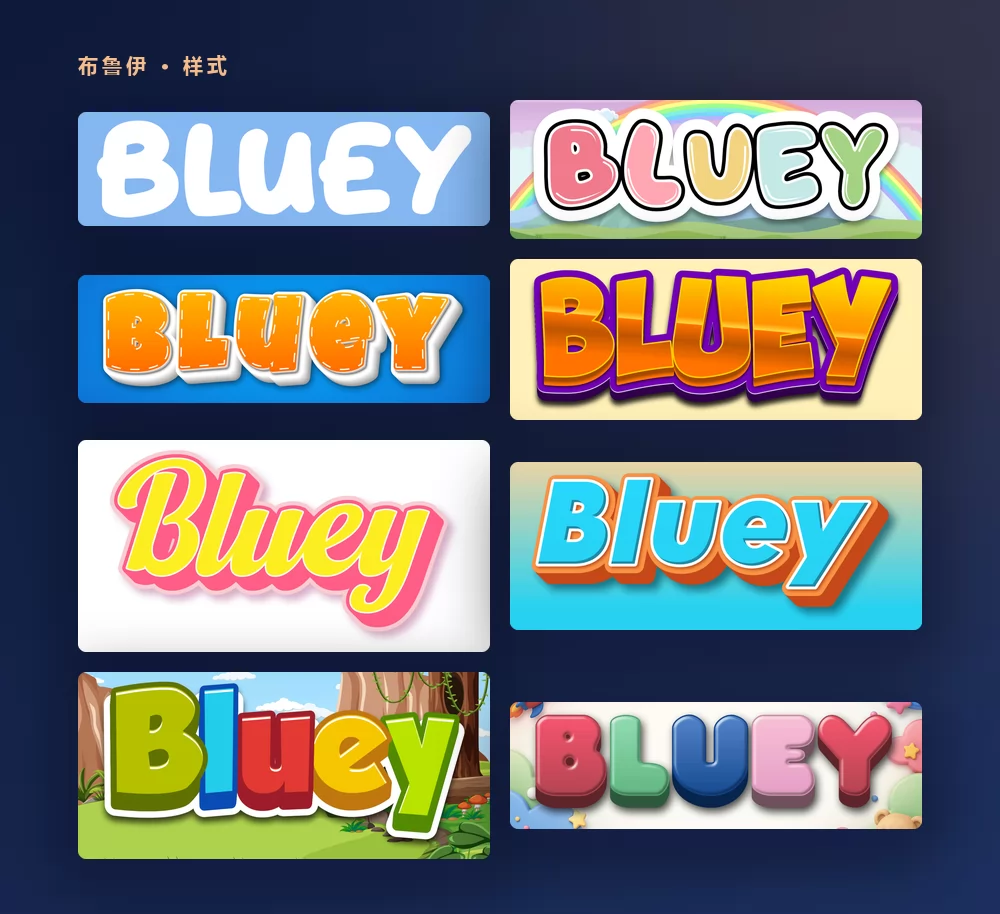
这些都来自同一个布鲁伊字体生成器,只是从列表里换了个样式。无需安装,无需账号。
关于布鲁伊字体
《布鲁伊》是一部面向学龄前儿童的澳大利亚动画剧集,由乔·布鲁姆创作,布里斯班的 Ludo Studio 制作。2018 年在 ABC Kids 首播,之后通过 BBC Studios 和 Disney+ 传遍全球。它讲的是六岁的蓝色澳洲牧牛犬布鲁伊、妹妹宾果和爸爸班迪特、妈妈奇莉的故事,一场场假装游戏里,总藏着一句给陪看的大人的人生道理。
剧集的标志是定制的手绘字样:粗壮、圆润、蹦蹦跳跳的大写字母,专为节目绘制,从未作为字体发布。其他地方用的字体,包括片头字卡、片尾字幕和官网,是 Hello Headline,由 Veneta Rangelova 设计、DearType 发行。2023 年《Bluey: The Videogame》上市时,标志下方的"The Videogame"用的也是 Hello Headline。这是一款商用字体。
至于外观相近的免费字体,在这个搜索词上排名靠前的网站列的都是同样三款:rockcake 的 Blue Custard,以及 Darrell Flood 的 Lovely Bubbles 和 Magical Markers。FG Studios 的 Heyam 是另一款接近的商用字体。
怎样做布鲁伊文字
第一步:输入名字
打开生成器,把示例文字换成你自己的:孩子的名字、"生日快乐"、教室的标签。字母会随着输入实时重绘。这个样式会自动全部转成大写,和标志一样。
第二步:挑一个样式
经典款是天蓝底上粗壮圆润的白色大写。在"样式"选项卡里,填充、描边和阴影可以分别调整,所以你可以保留蹦跳的字形,把颜色换到别处:宾果主题派对用橙色,或者淡粉色、彩虹色。
第三步:选好尺寸
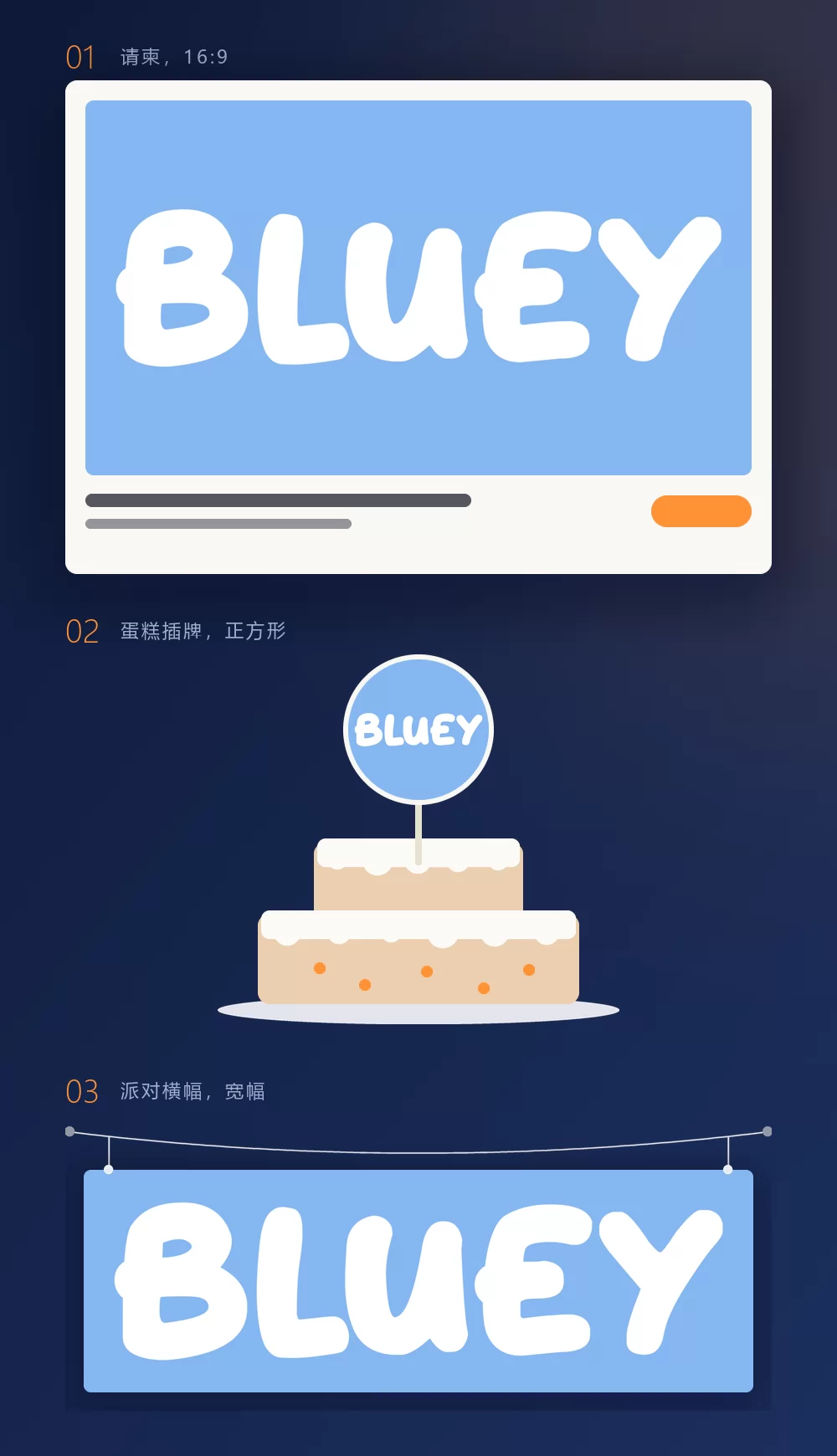
导出前先设好尺寸,之后就不用再裁。请柬用 16:9,蛋糕插牌或纸杯蛋糕签用正方形,挂在墙上的横幅用宽条。上面三个情景模拟,就是这些尺寸打印出来之后的样子。
第四步:下载
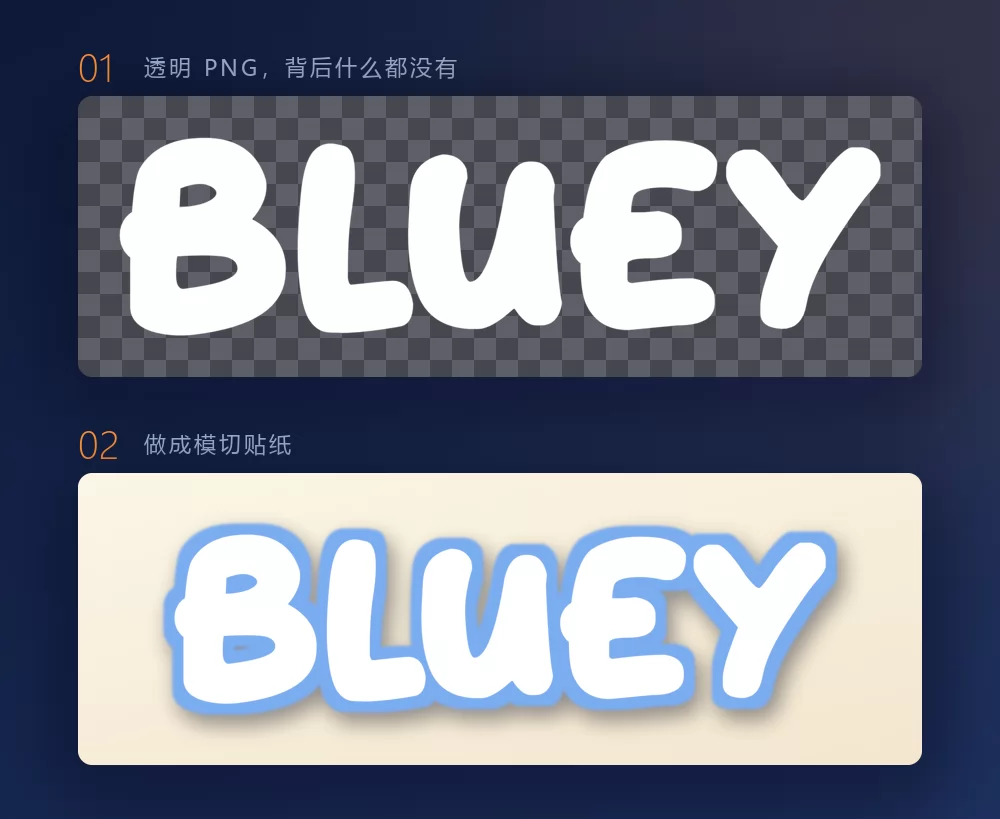
如果打算把名字放到自己的设计上,就在"下载"选项卡里选透明 PNG。这是大多数人错过的选项,而对派对打印品来说恰恰是最要紧的:你自己的纸,名字在上面,周围没有蓝色方框。它也是切割机做模切贴纸或插牌时需要的东西:字母的形状就是切割的形状。
名字一长,宽度很快就满了
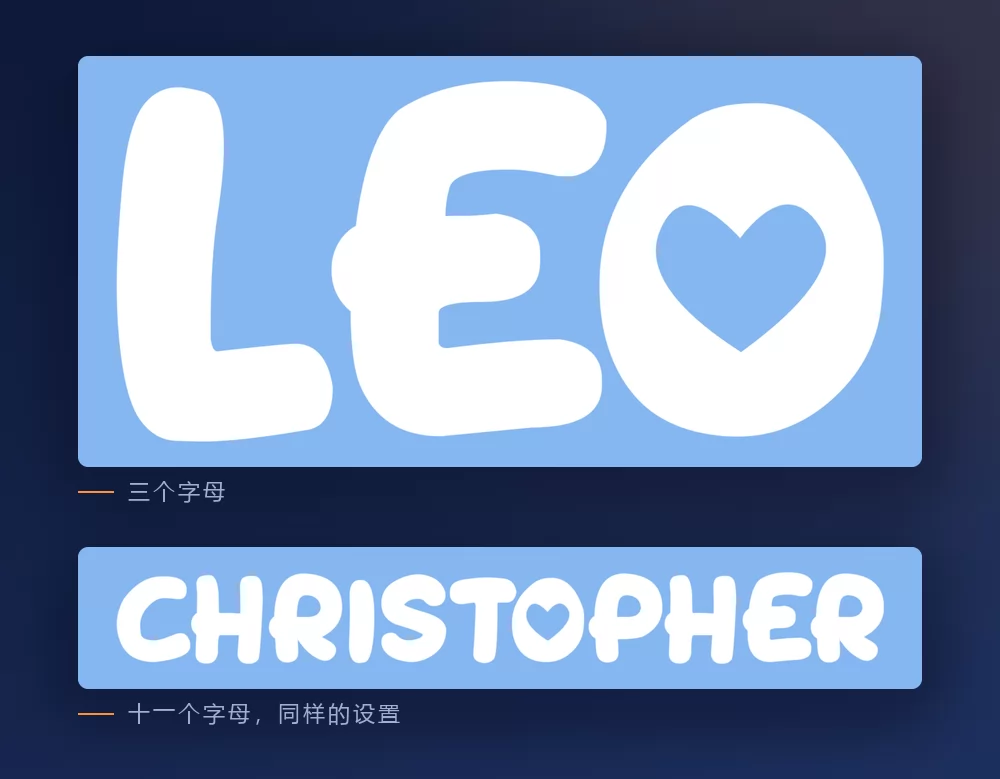
字母越多,排得越紧。字间距是"文字"选项卡里的滑块:稍微拉开一点,长名字就不再显得局促。同一个选项卡里还有缩放、行高、弧度和旋转。
布鲁伊风格,还是游戏房风格
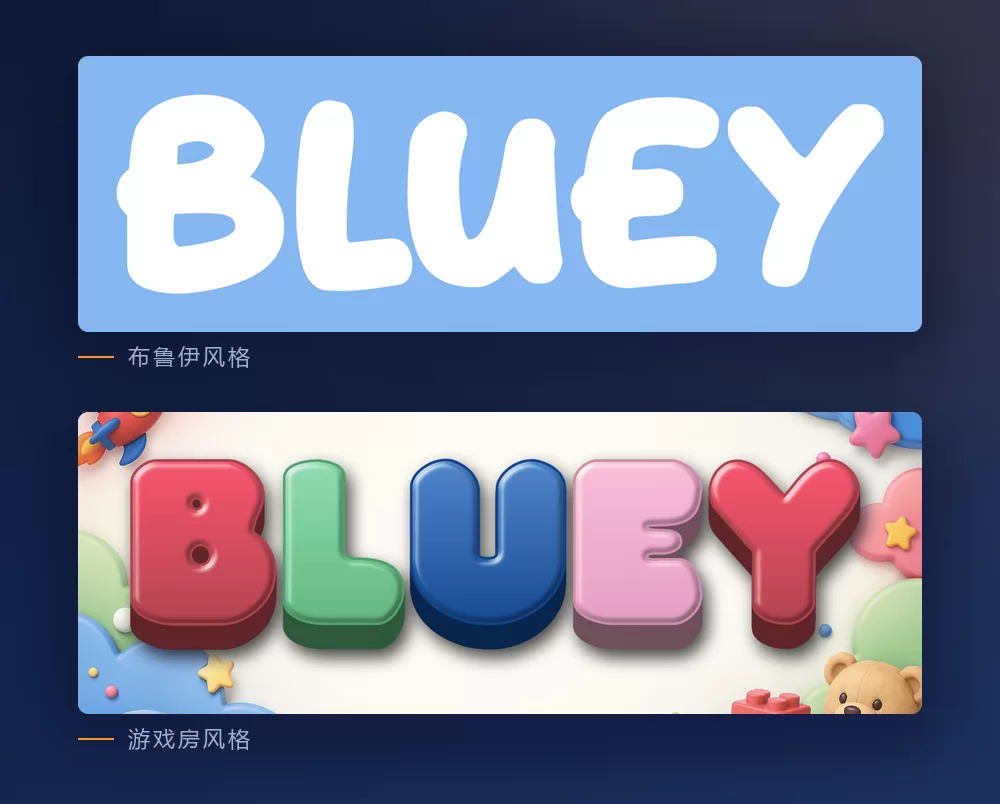
布鲁伊风格就是标志本身:白色、粗壮、圆润、带点蹦跳感,衬在那种天蓝色上。大多数人想到的就是它,布鲁伊主题生日会要的也是它。
游戏房风格是粉彩色的圆润塑料字母,周围散落着玩具。它不带任何剧集标识,所以更适合儿童房的墙面,或者不做主题的周岁生日。游戏房字母生成器里有现成的预设。
想安装字体的话,选哪一款
标志本身不是字体。它是定制字样,所以任何叫"布鲁伊字体"的文件,都是别人对它的再现。
Hello Headline 是剧集其余部分的真正答案。它是 DearType 的商用字体,在字库公司购买下载。想要片头字卡和片尾字幕的精确效果,就是它。
Blue Custard,rockcake 所作,是最接近标志那种蹦跳大写的免费字体。它在 DaFont 上以捐赠软件形式发布:可以自由使用,欢迎给设计师打赏。
Lovely Bubbles 和 Magical Markers,都是 Darrell Flood 所作,是每份清单都会列出的另外两款。Lovely Bubbles 标注为个人使用免费,Magical Markers 为捐赠软件,两者都在 DaFont 上。
做客户项目、授权必须干净时,老实的选择是 Google Fonts 上开放授权的圆体:Fredoka,神韵上最接近,粗细齐全;Baloo 2 和 Sniglet。三款都不是布鲁伊字体,但都能给你那种亲切圆润的感觉,授权没人能挑刺,而且在 Canva 里就能用。
大家真正用它做什么
下载页面会列出"最佳用途",而它们和实际做出来的东西一致:生日请柬、蛋糕和纸杯蛋糕插牌、挂满整面墙的横幅、派对用的名牌、给小寿星的 T 恤、教室标签和欢迎牌。几乎都是打印出来的,也几乎都用透明 PNG 比装字体效果好,因为这个效果就是白色字母配上那种精确的天蓝色,而字体文件只给你轮廓,别的什么都没有。
怎样在 Canva 里做布鲁伊文字
Canva 没有 Hello Headline,但有 Fredoka,所以不用离开 Canva 也能得到圆润的感觉,只是那不会是标志。要精确的标志效果,就把字样做成透明 PNG 再上传:它能直接放进 Canva 的请柬里,而且在打印尺寸下依然清晰。
怎样在 Photoshop 里做布鲁伊文字
安装 Blue Custard 或 Fredoka,用大写输入名字,然后用图层样式搭出效果:
- 颜色叠加,白色。
- 描边,位置外部,用比背景稍深一点的蓝色,细一些。
- 一层天蓝色背景,和标志同一个色调:浅、略带灰,绝不刺眼。
不要渐变,不要发光。整个效果就是那种蓝色上的白字,每多加一个效果,就离剧集远一步。
怎样在 Word 里做布鲁伊文字
安装字体,用大写输入名字,把字母设成白色,后面放一个天蓝色形状。这个样式需要的就这些,Word 做得到。请柬和其他要打印的东西,用导出的 PNG 还是会更干净。
在手机上
常见问题
布鲁伊标志用的是什么字体? 没有字体。它是专为剧集绘制的定制字样,从未作为字体发布。Blue Custard 是最接近的免费再现。
布鲁伊用的是什么字体? Hello Headline,DearType 的 Veneta Rangelova 设计,用于片头字卡、片尾字幕和官网。它是商用字体。
我能用它做布鲁伊蛋糕插牌吗? 能。选正方形尺寸,下载透明 PNG,打印后沿字母轮廓剪下,或者把 PNG 发给切割机。
做请柬时怎样得到透明背景? 在"下载"选项卡里选透明 PNG,然后把名字放到你自己的纸张、照片或打印稿上。
为什么我的文字和真正的标志比起来不对劲? 通常是蓝色的问题,不是字体。标志衬在浅浅的、略带灰的天蓝色上。换成刺眼的电光蓝,或者加了渐变,它就不像布鲁伊了。